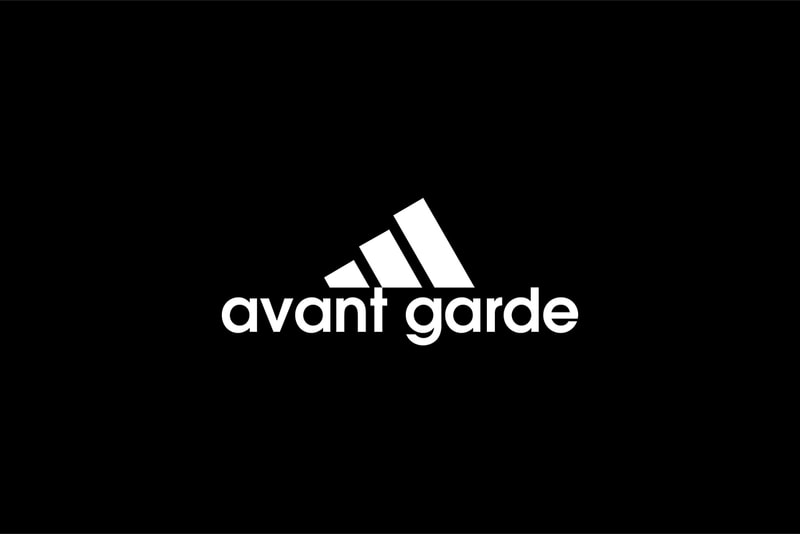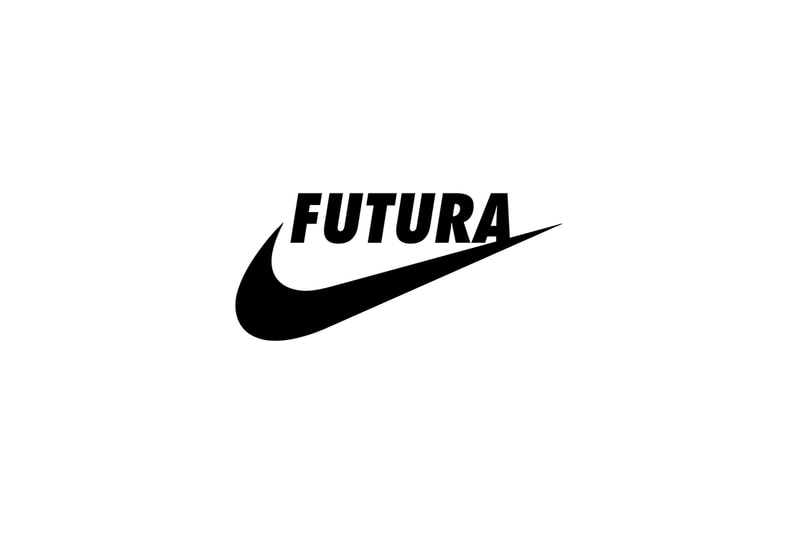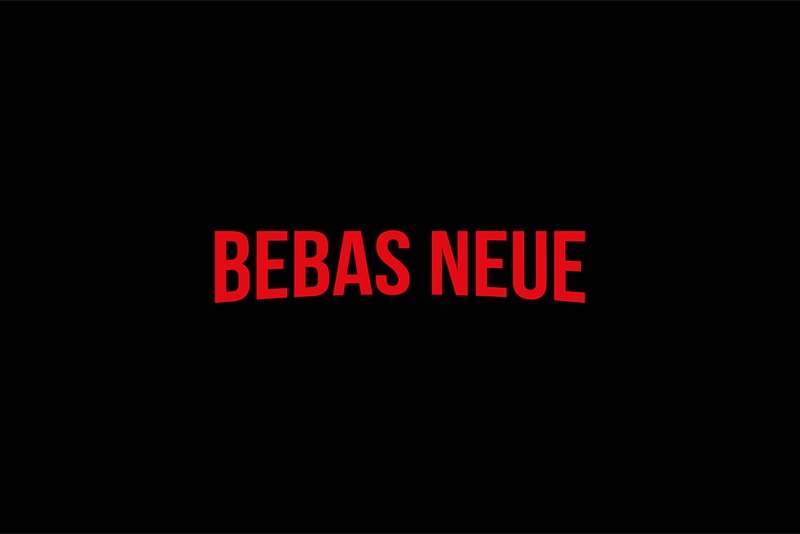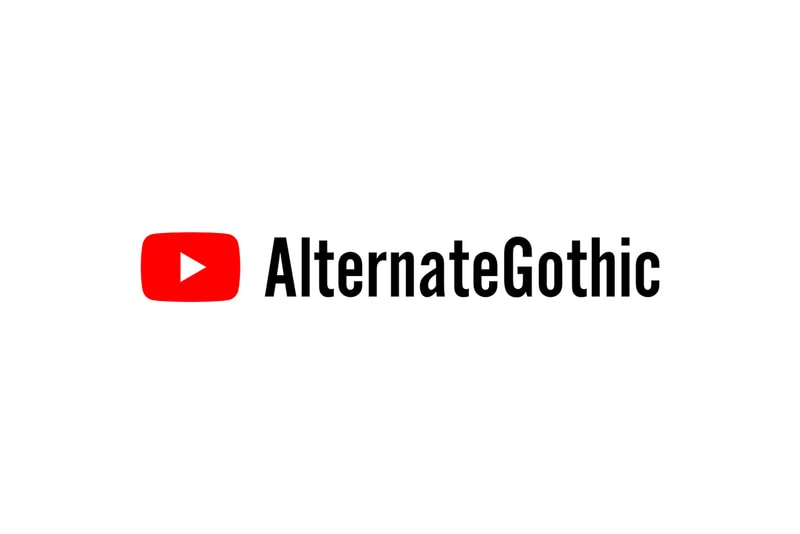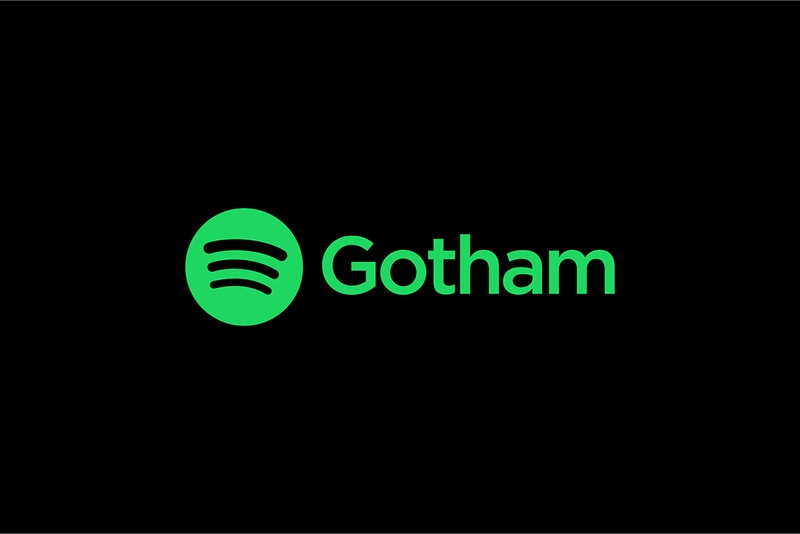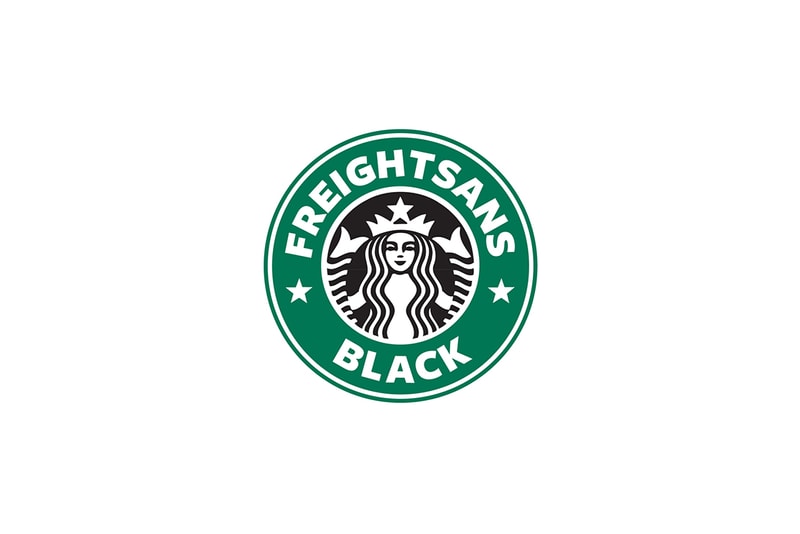
브랜드 로고를 폰트 이름으로 대체해도 알아볼 수 있을까?
아디다스인 듯 아디다스 아닌 아디다스 같은.
브랜드 로고 & 아이덴티티 디자이너 임마뉴엘 아브라테(Emanuele Abrate)가 최근 아주 흥미로운 실험을 했다. 아디다스부터 레드불까지, 지구상에서 가장 유명한 브랜드 로고들을 변형한 것. 로고 디자인에서 브랜드명을 서체 이름으로 대체해도 사람들이 알아볼 수 있는지 알아보기 위해서였다. 가령 와츠앱 로고의 ‘WhatsApp’을 ‘HelveticaNeue’로 대체하는 식이다. 이런 기발한 아이디어는 어디에서 왔을까? 아브라테는 프로젝트가 아주 흔한 질문에서 출발했다고 설명한다. 로고를 볼 때마다, “저 서체는 뭐지? 어떻게 생겼는지, 어떻게 디자인되었는지, 어떤 종류의 서체를 사용했는지, 왜 사용했는지 궁금했다.” 그는 브랜드 로고에 대한 분석을 그래픽 프로젝트로 발전시키기로 했다.
결과는 놀랍다. 아브라테가 새롭게 디자인한 로고는 낯설지만 낯설지 않다. 브랜드 이름이 빠져있다는 사실조차 알아채기 힘들 정도. ‘Neflix’와 전혀 다른 ‘Bebas Neue’ 같은 문구도 자연스럽게 넷플릭스 로고로 인식된다. ‘klavika’ 역시 ‘Facebook’과 무관하지만 페이스북 로고인지 알아챌 수 있는 것이다. 우리의 뇌는 로고의 마크, 컬러, 서체들이 어우러져 생성하는 문맥에 훈련받기 때문에 로고의 문구가 바뀌어도 기존에 인지하고 있던 브랜드 로고로 인식하는 것이다. 상징적인 로고 디자인에 있어 타이포그래피가 가지는 중요성에 관해서 설명하는 아브라테의 작업들을 위에서 감상해보자.